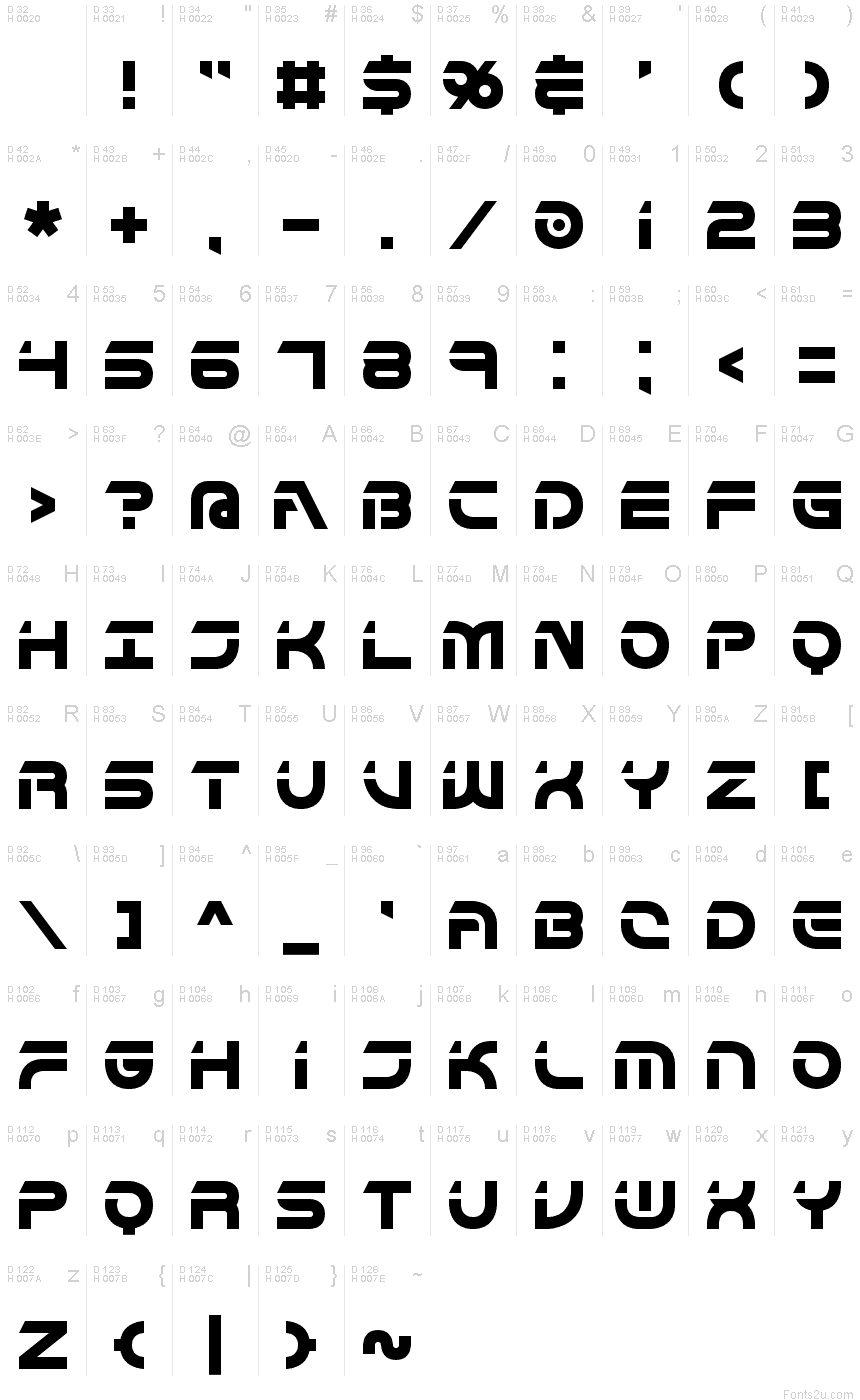
Flipside BRK od Aenigma Fonts to darmowy, futurystyczny krój displayowy o wyrazistym, modułowym charakterze. Jego masywne litery o niskim profilu wyglądają, jakby zostały wycięte z arkusza błyszczącego czarnego plastiku, a płaskie wierzchołki i gładkie wewnętrzne łuki sprawiają, że czcionka jest odważna, a jednocześnie zaskakująco opływowa. Ciasne światło między znakami tworzy ciągły, niemal mechaniczny rytm, który natychmiast kojarzy się z sci-fi i nowoczesnymi technologiami.
Flipside BRK pozwala nadać silny, spójny wyraz tytułom gier, drużynom e-sportowym, okładkom muzyki elektronicznej, plakatom tech, makietom interfejsów i eksperymentalnym logotypom. Ten darmowy font najlepiej sprawdza się w dużych rozmiarach, gdzie jego ostre cięcia i szerokie formy mogą w pełni wybrzmieć; w tekście głównym zestaw go z czystym, geometrycznym bezszeryfowcem, aby zachować czytelność przy jednoczesnym utrzymaniu tego eleganckiego, futurystycznego stylu.